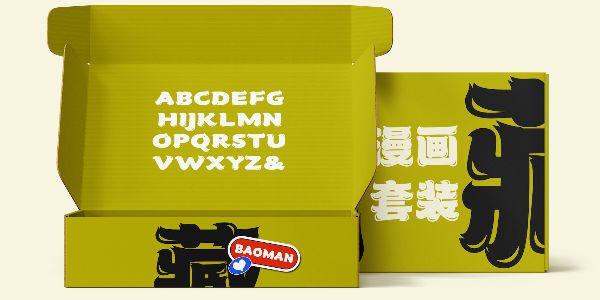
专为暴走漫画而生的一款字体
艺术字体—设计字体
漫画 / 个性 / 豪放
标志 / 书籍 / 广告 / 杂志 / 动漫 / 游戏 / 影视 / 包装
汉仪暴漫体是一款个性另类的漫画风格标题字体。暴走漫画,是一种流行于网络的开放式漫画,题材往往是日常生活中的糗事囧事。汉仪暴漫体有着和暴走漫画同样夸张醒目的风格和混沌的魅力,在简单直接的画风中包含丰富的细节,极具表现力。这款令人过目难忘的标题字体适合应用于漫画、影视、广告、包装等需要抓人眼球的使用场景。
作为一款大声量标题字体,汉仪暴漫体的字形饱满,字面接近正方形,整体粗重而充实,接得住各种暴走的情绪!
汉仪暴漫体粗厚浑圆的笔画细节丰富而极具表现力。笔画起笔和收笔的设计带有装饰性的笔锋,在精致的字形中还原了暴走漫画的笔触和质感。
漫画风格的高光为充盈的笔画增加了呼吸感,使得这款字体满而不溢,排版效果更生动。
汉仪暴漫体的西文部分保持了与中文部分一致的设计语言,字形方整饱满,强调笔画的装饰性细节。